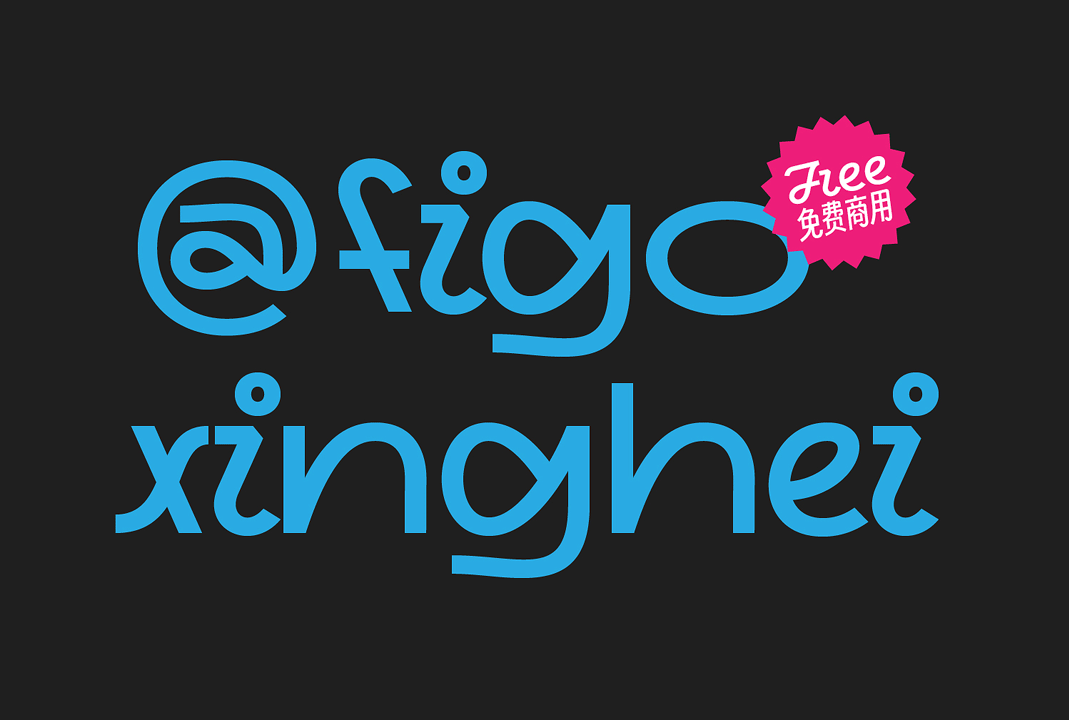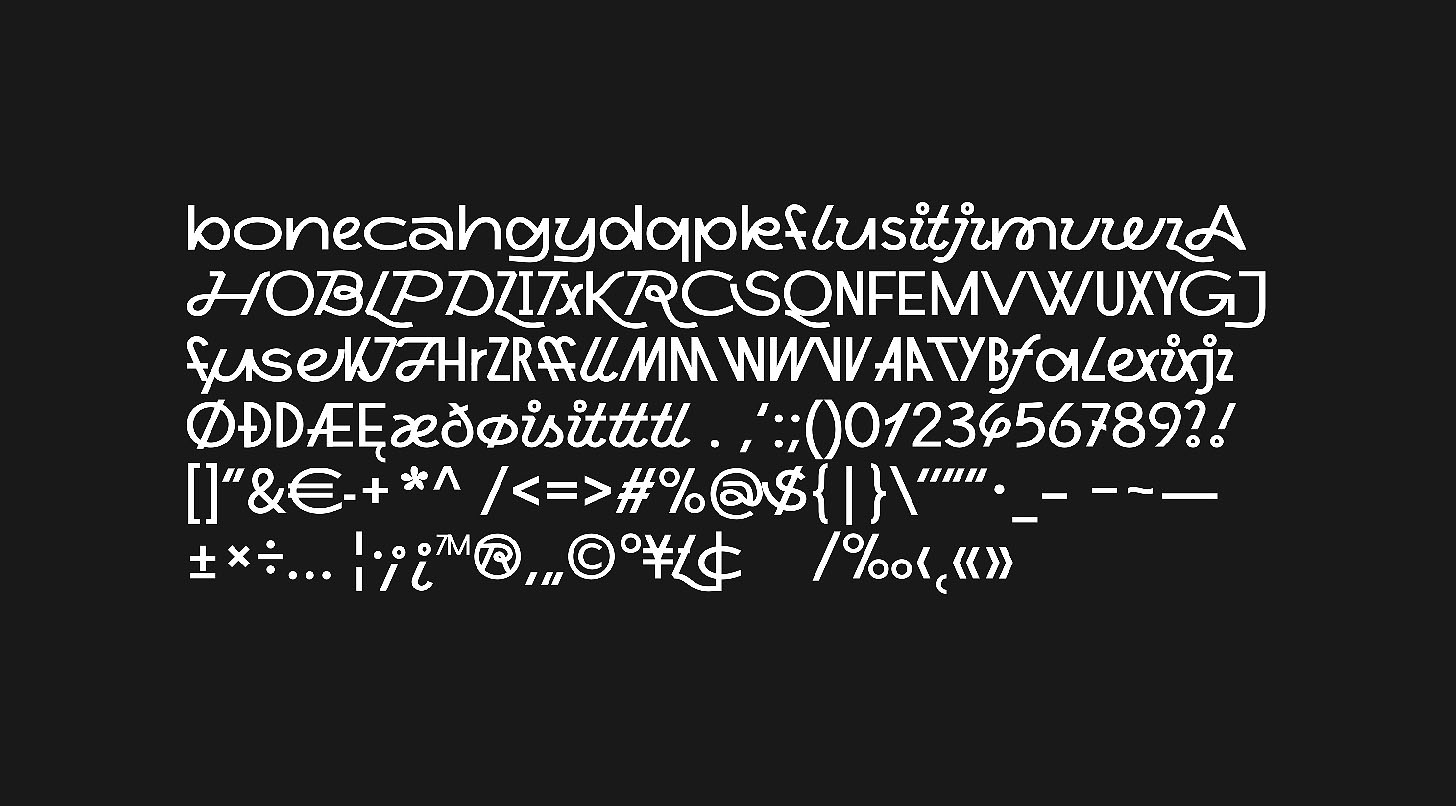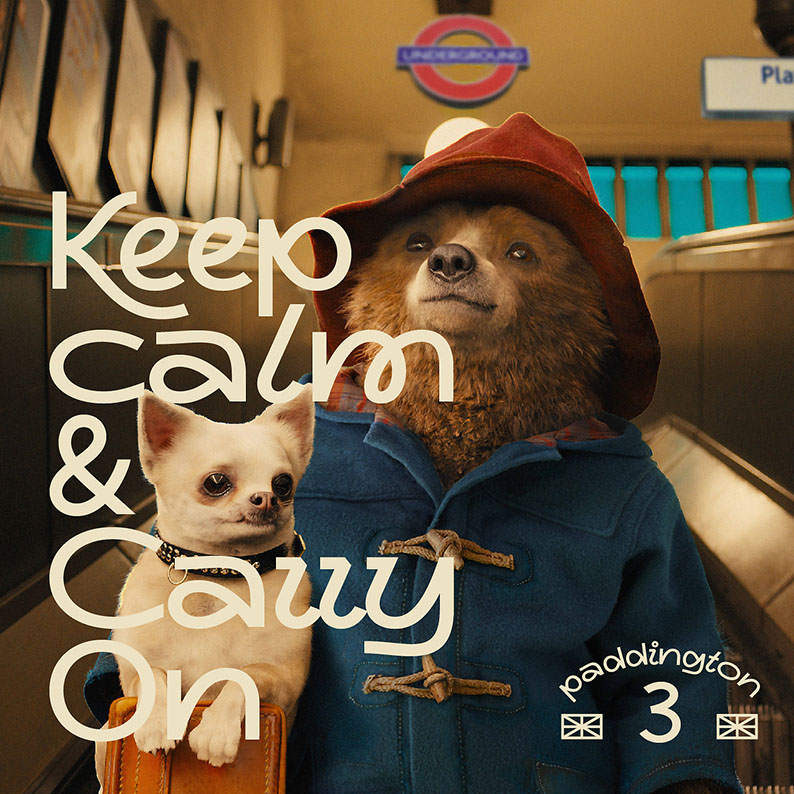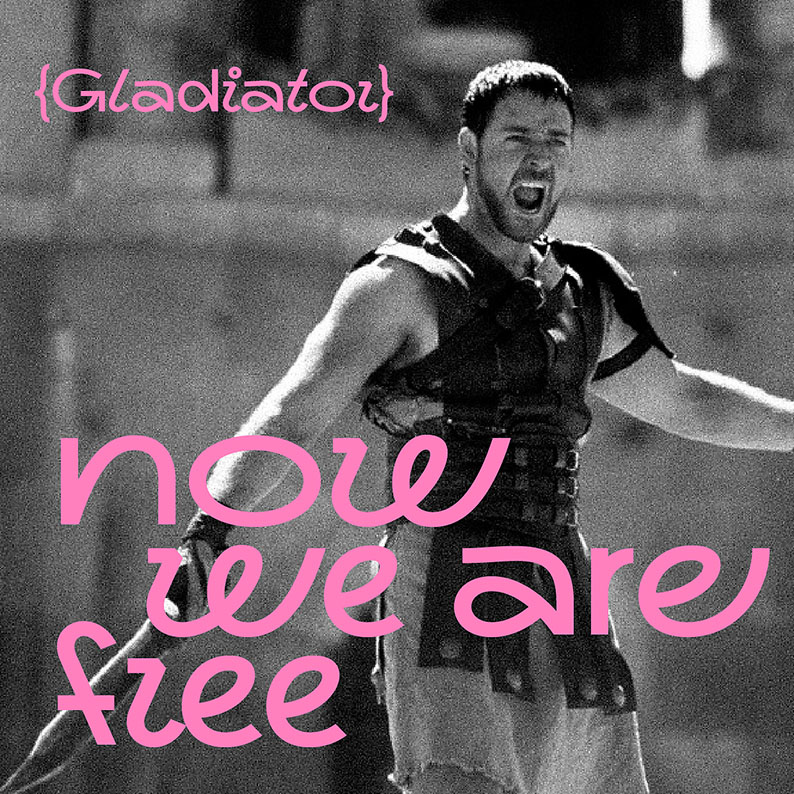
行黑 xinghei (figo_xinghei) 免费商用英文字库下载
行黑/xinghei(figo_xinghei.otf)是由站酷设计师figovision(UID:1042506)创作的一款免费可商用英文字体。
行黑/xinghei(figo_xinghei.otf)字体气质独特,非常适合在艺术、标题等场景中使用。